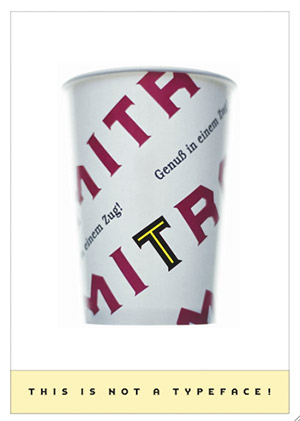
Sammelkarte: Pullman, der SchriftzugEine Fontcard vom Oktober 1997, gestaltet von Factor Design. Sie
zeigt die Firmenschrift der 1916 in Berlin gegründeten
Mitteleuropäischen Schlaf- und Speisewagen Aktiengesellschaft (kurz
MITROPA), als FF Pullman in digitaler Form neu interpretiert. Johannes
Erler hat sie mit seinem Büro Factor Design zu einer
vielseitigen Headline-Familie ausgebaut. Weiterlesen ...
![]() Geburtspate der Schrift FF Pullman war ein Mitropa-Pappbecher, so
wie er kurz nach der Wende in fast allen Speisewagen der Deutschen Bahn
zu finden war. Hintergrund: Bis Mitte der 30er Jahre schwärmte ganz Europa
von den bequemen Schlafwagen der Mitropa. Die Teilung Deutschlands spaltete auch
den Schienen-Dienstleister in Deutsche Schlafwagen- und
Speisewagen-Gesellschaft (DSG) für den Westen der Nation, in der DDR
überlebte der alte Name und sein Schriftzug.
Nach der Wende wurden beide Unternehmen unter der Dachmarke Mitropa wiedervereint, die Mitte der 90er-Jahre ihre alte Popularität erreichte. Dann begann der europäische Wettbewerb auf den Schienen und die Deutsche Bahn änderte jährlich ihre Service-Strategie. Die Marke Mitropa gerät ins Hintertreffen. Man begegnet ihr immer seltener. Seit April 2004 gehört sie dem internationalen Foodservice-Unternehmen Compass. ![]() Der kräftige, kantige Mitropa-Schriftzug lädt zu Spielereien ein. Johannes Erler ließ sich sofort von einer Inline-Version inspirieren, die den fetten Buchstaben Leichtigkeit gibt; mit Hilfe des Layer-Schnitts lassen sich durch Überlagerung zweifarbige Schriftzüge erstellen. Alten Fahrplänen entnahm er sympathische Symbole zu Gastronomie, Verkehrsmittel und Wegweisung. Die Schnitte der FF Pullman probesetzen ... ![]() Font-Sammelkarte FF Pullman (© FSI FontShop International), Gestaltung: Factor Design, Hamburg. Sammelkarte FF Pullman als PDF downloaden ... (200 KB) Herausgegeben: Fr - September 16, 2005 at 12:33 vorm. | |